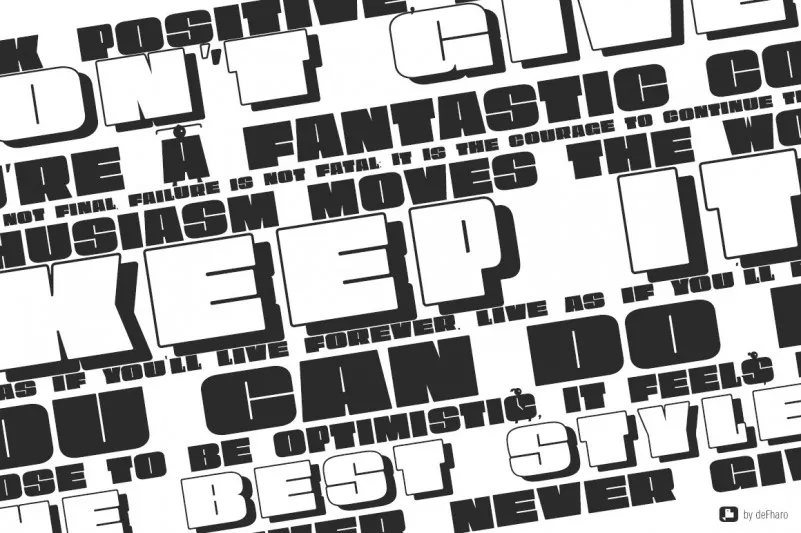
A OBESUM CAPS Typeface é uma mistura única entre a simetria geométrica e a contraste notável dos espaços internos ou ‘counterforms’. Essa tipografia foi criada em homenagem às letras maiúsculas, não apenas como símbolos de importância, mas também àquelas que exibem a característica peculiar das meninas obesas – as curvas e formas redondas que contrastam com o tamanho generoso desses indivíduos. A OBESUM CAPS apresenta linhas sólidas e claras, com uma forte geometria que destaca suas características distintas. Seu estilo decorativo encaixa-se perfeitamente para ambientes onde a atenção à detalhe é valorizada, como design de logotipos, publicidade de moda ou arte gráfica minimalista. A fonte OBESUM CAPS não apenas se sobressai por sua forma elegante e contrastada, mas também por seu caráter original que chama a atenção com a mescla inusitada de formas geométricas e curvas redondas.